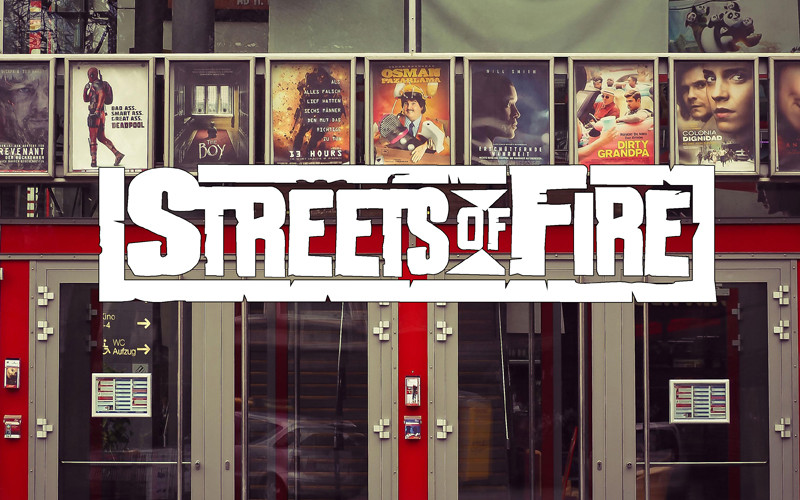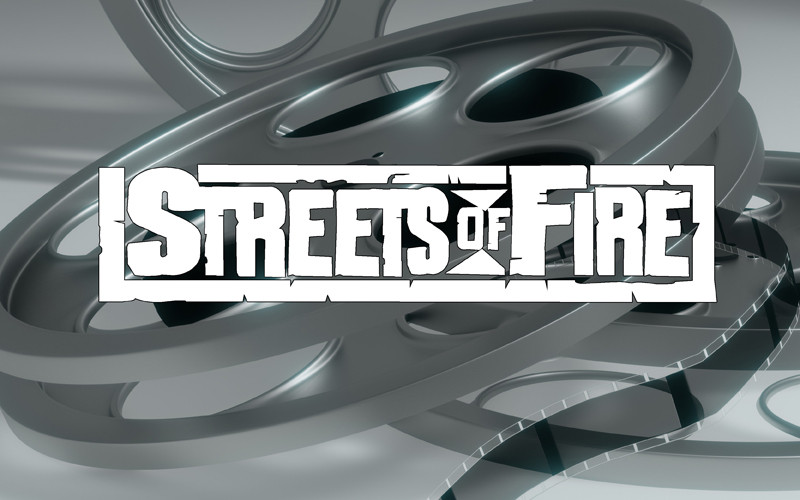
Directly from the film directed by Walter Hill and starring Diane Lane, the new font for all fans of the film.
Strade di Fuoco Font
Direttamente dal film diretto da Walter Hill e interpretato da Diane Lane, il font inedito per tutti gli estimatori del film.